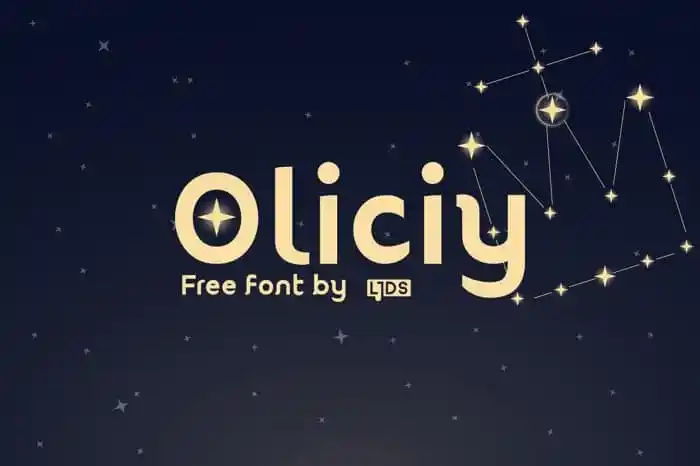
Oliciy Sans Serif Font – Download Grátis
A Oliciy Sans Serif é uma fonte que oferece tudo o que você precisa para projetos digitais modernos. Com versões tanto do alfabeto maiúsculo quanto minúsculo, esta fonte também inclui sinais de pontuação, números, símbolos e simbolos web, além de suporte a múltiplas línguas. Perfeita para qualquer projeto que exija uma aparência limpa e moderna, seja um logotipo ou criação de marca, a Oliciy Sans Serif é uma escolha ótima. Combinada com outros elementos gráficos, ela adicionará uma dose extra de elegância ao seu design digital. Seja para websites, cartões de visita ou qualquer outro uso em que você deseje incorporar um ar contemporâneo e minimalista, a Oliciy Sans Serif é o elemento perfeito.